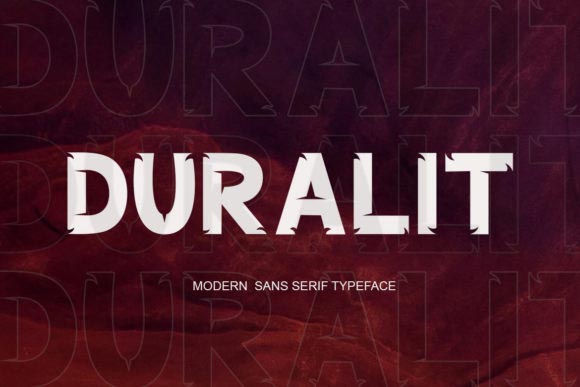
دانلود فونت انگلیسی سنس سریف Duralit
Duralit یک فونت serif جسورانه است و متنوع و متنوعی را در خود جای داده است. شخصیت های پرتحرک آن باعث می شود پروژه شما از برجسته خارج شود! تنها محدودیت تخیل شما است!
Duralit is a bold sans serif font, fitting a wide variety of designs. Its chunky characters will make your project stand out! The only limit is your imagination!